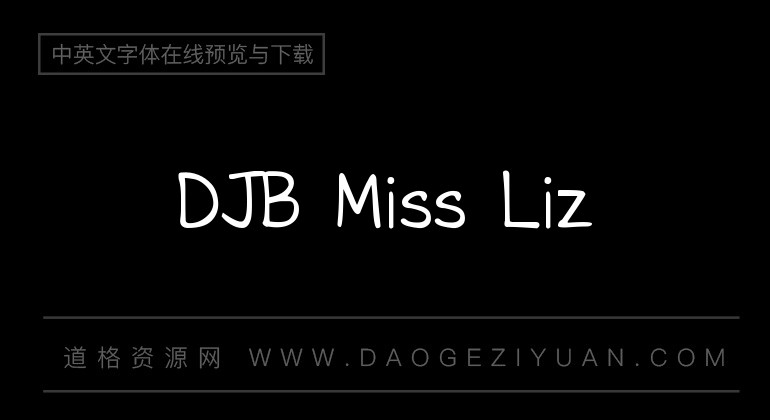
DJB Miss Liz是一款手写风格的字体,设计者为DJ Inkers公司的Liz博士。它的特点是有点像小学生用铅笔书写的字体,有点圆润,有点丰满,相对来说比较温和和可爱。这款字体有两种风格,一种是常规的字体,另一种是加粗版,可以用于突出一些重要的内容或者标题。DJB Miss Liz字体适合应用于儿童书籍、教育材料、明信片、海报等设计领域,它可以给人一种亲切和友好的感觉。内容介绍
DJB Miss Liz是一款非常不错的手写艺术字体,具有很好的视觉感,适合于文化类的宣传设计、商业类品牌的广告和产品包装设计以及个性化文字排版等较多场景。